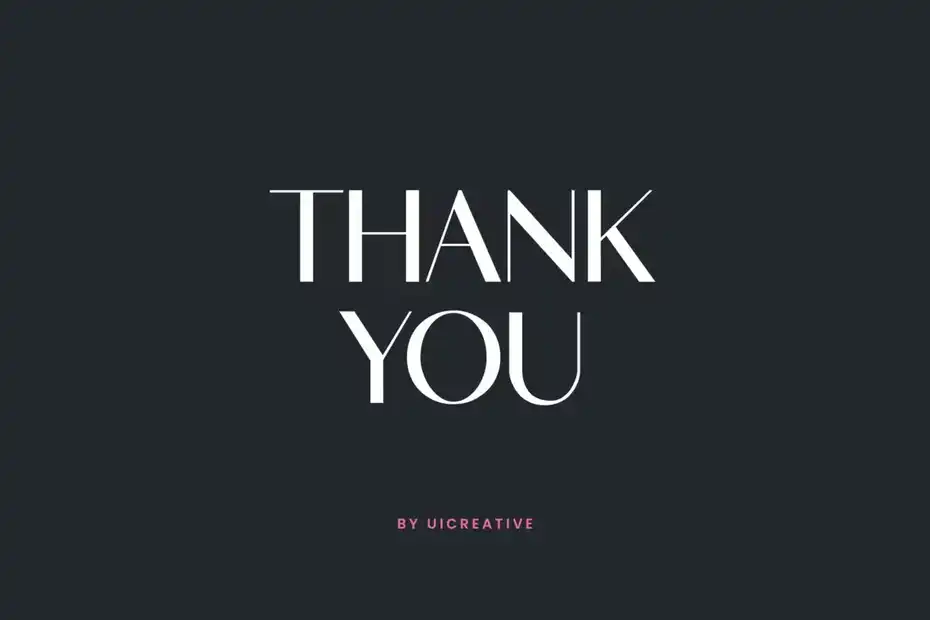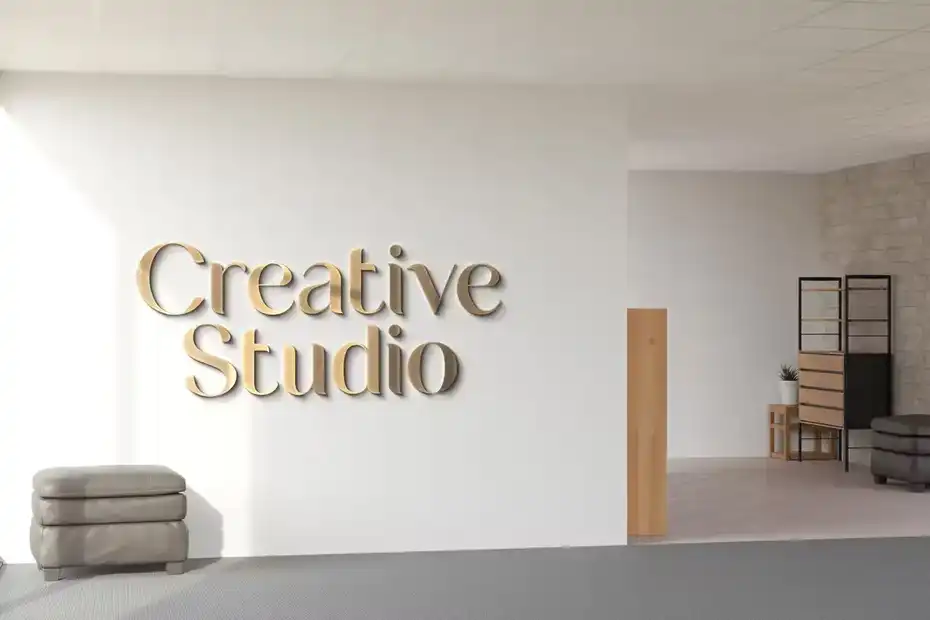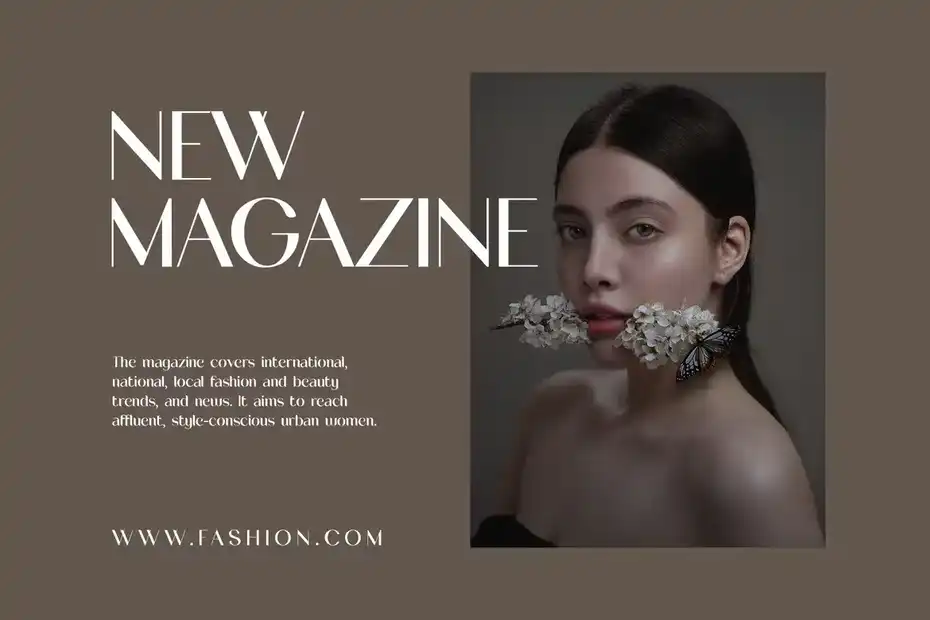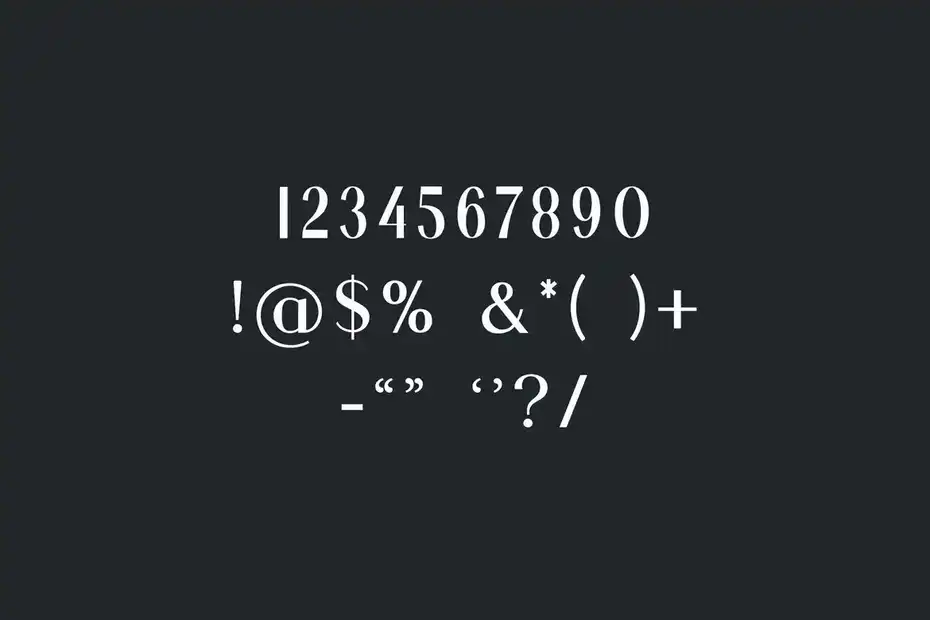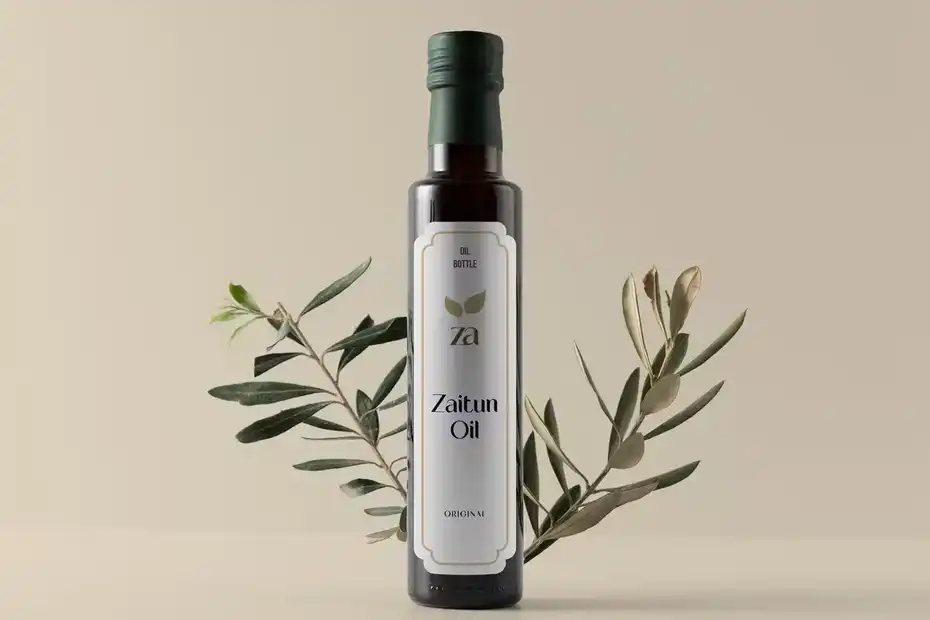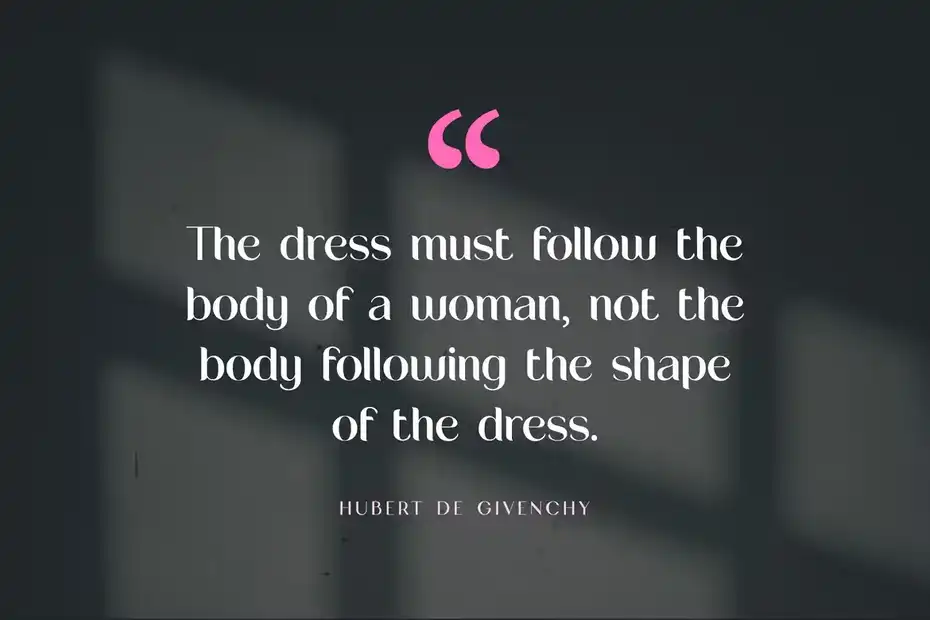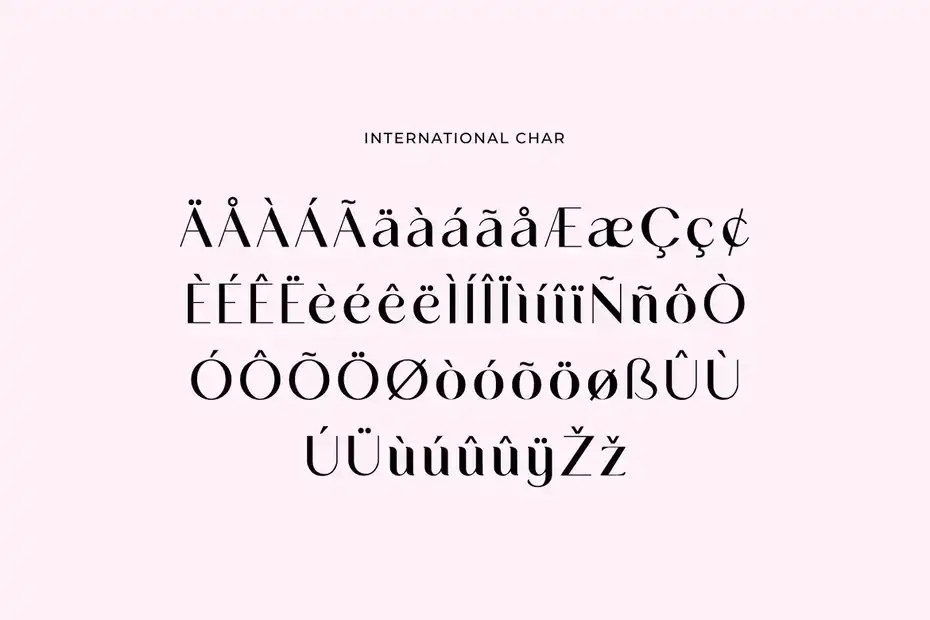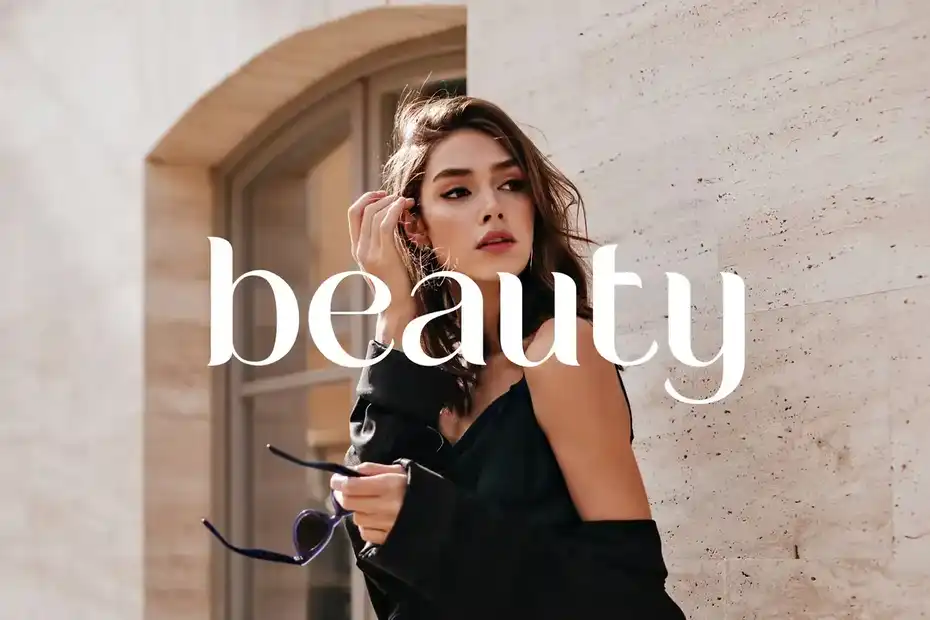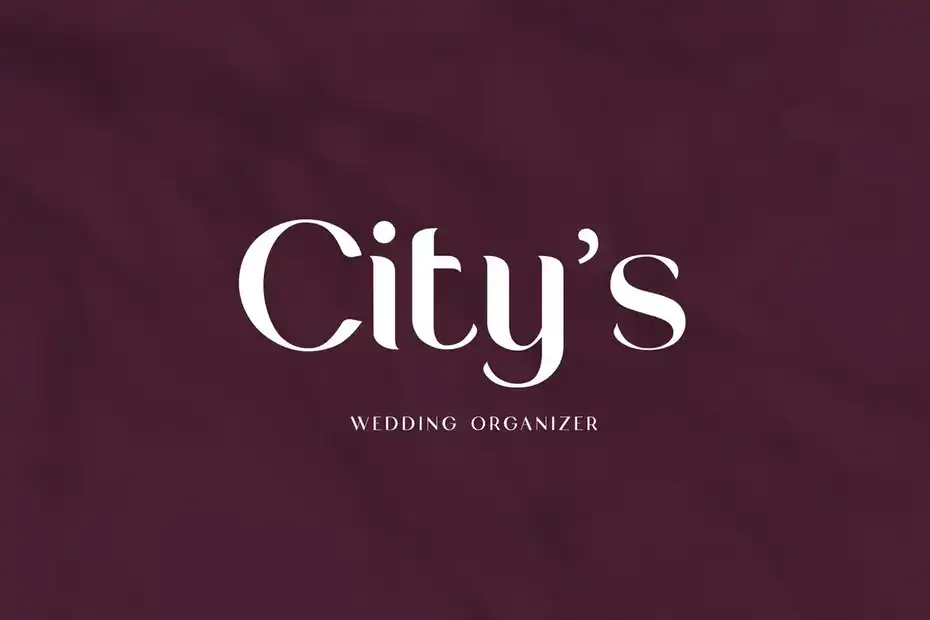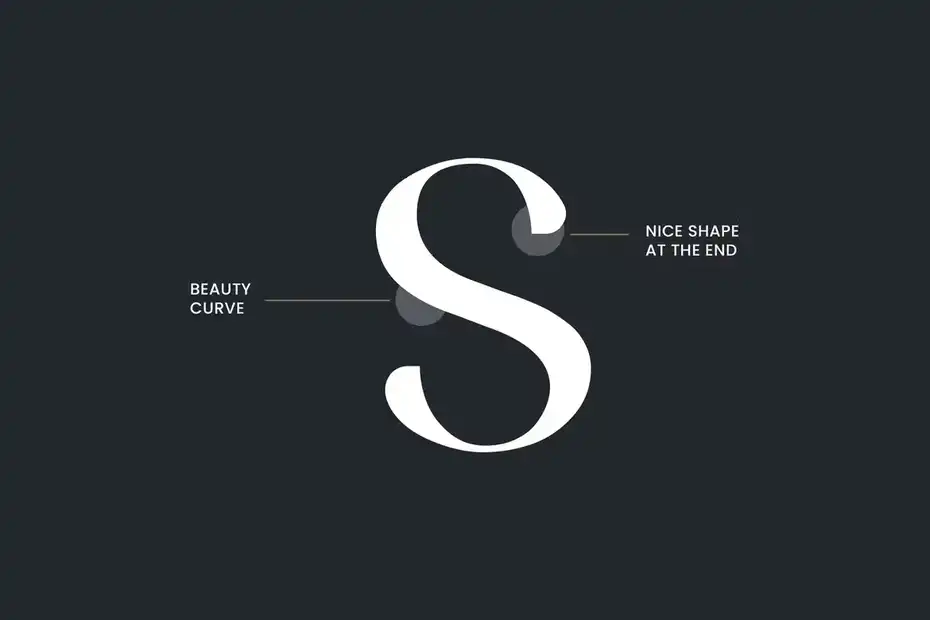
دانلود فونت لوکس Waylimo Luxury Sans Serif Font
دانلود فونت لوکس Waylimo Luxury Sans Serif Font : این فونت یک فونت انگلیسی مدرن Sans Serif است که برای پروژه های مختلف مانند: امضا، برندینگ، لوگو، عروسی، نقل قول تایپوگرافی، جلد مجلات یا کتاب، سربرگ وب سایت، لباس، طراحی بسته بندی و غیره مناسب میباشد.